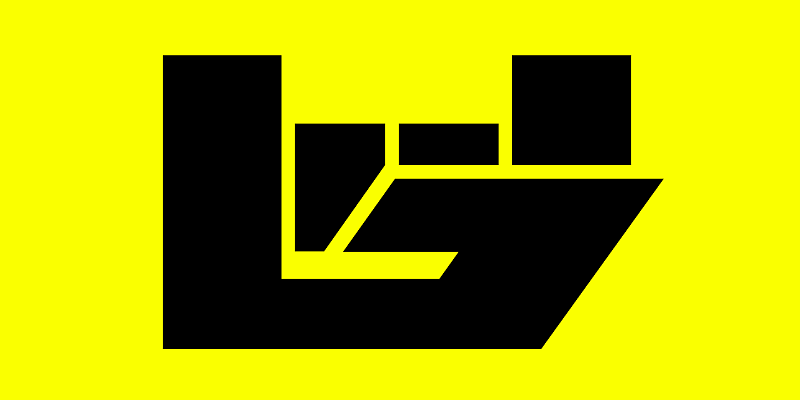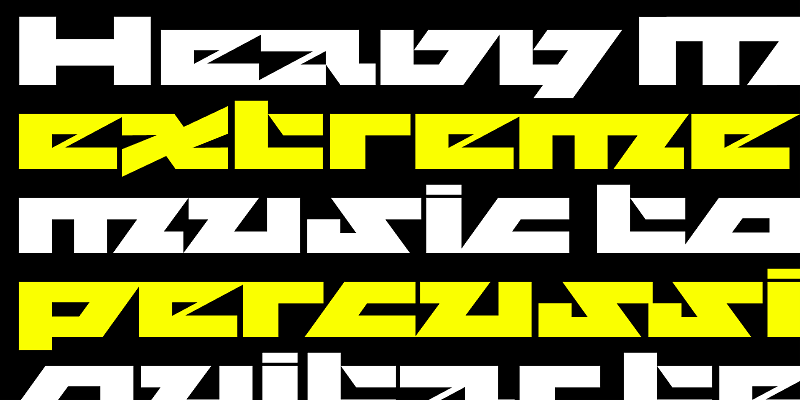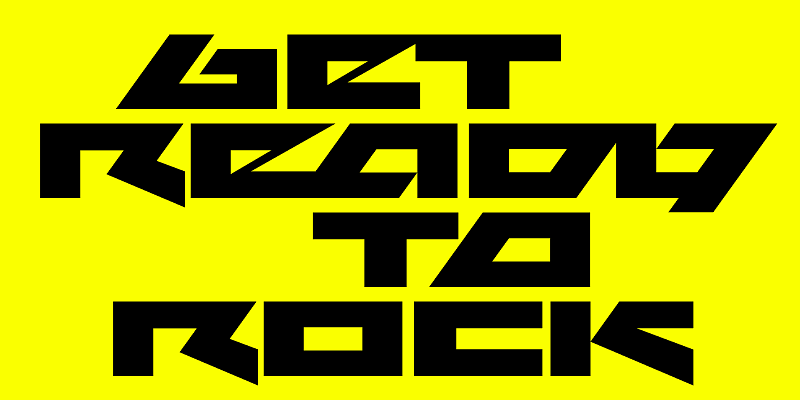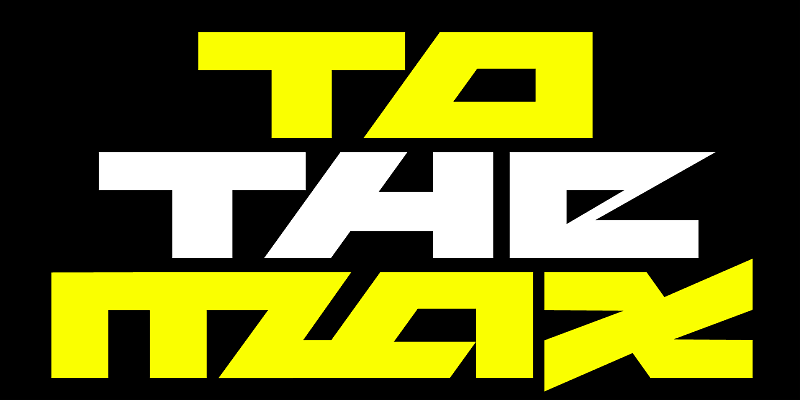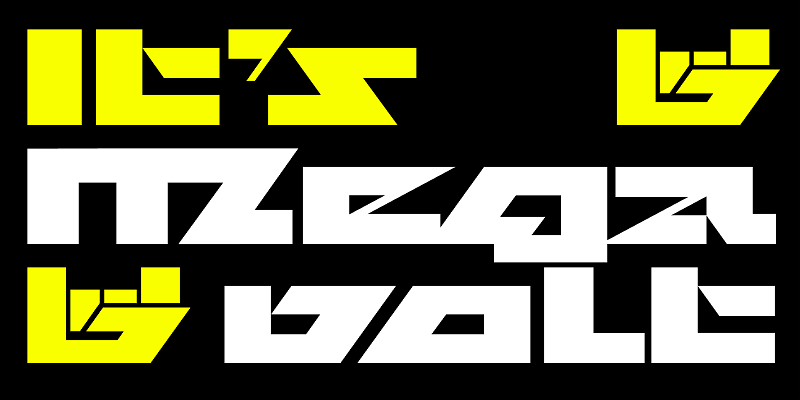
Megavolt es una sans serif ancha sin curvas. En su lugar, se basa en una intrincada red de trapecios y ángulos de 54° para comunicar contundencia, intensidad y movimiento. Después de comenzar con el tipo de letra como un ejercicio geométrico formal, rápidamente comprendí que necesitaba apoyarme en sus connotaciones de ciencia ficción y metal. El resultado son formas de letras tan severas e intransigentes que desafían la legibilidad, ¡por no mencionar el buen gusto!
David Jonathan Ross dibuja letras de todas las formas y tamaños para diseños de tipografías comerciales y personalizados en su estudio en los bosques del Oeste de Massachusetts. Nacido en Los Ángeles, empezó a crear tipografías en el Hampshire College y se unió a The Font Bureau en 2007, donde perfeccionó sus habilidades en el trazado de curvas de Bézier. Hoy en día publica sus diseños de fuentes en su propia compañía tipográfica, DJR, y además trabaja en proyectos con Type Network y desarrolla tipografías de gran formato singulares para su Font of the Month Club.